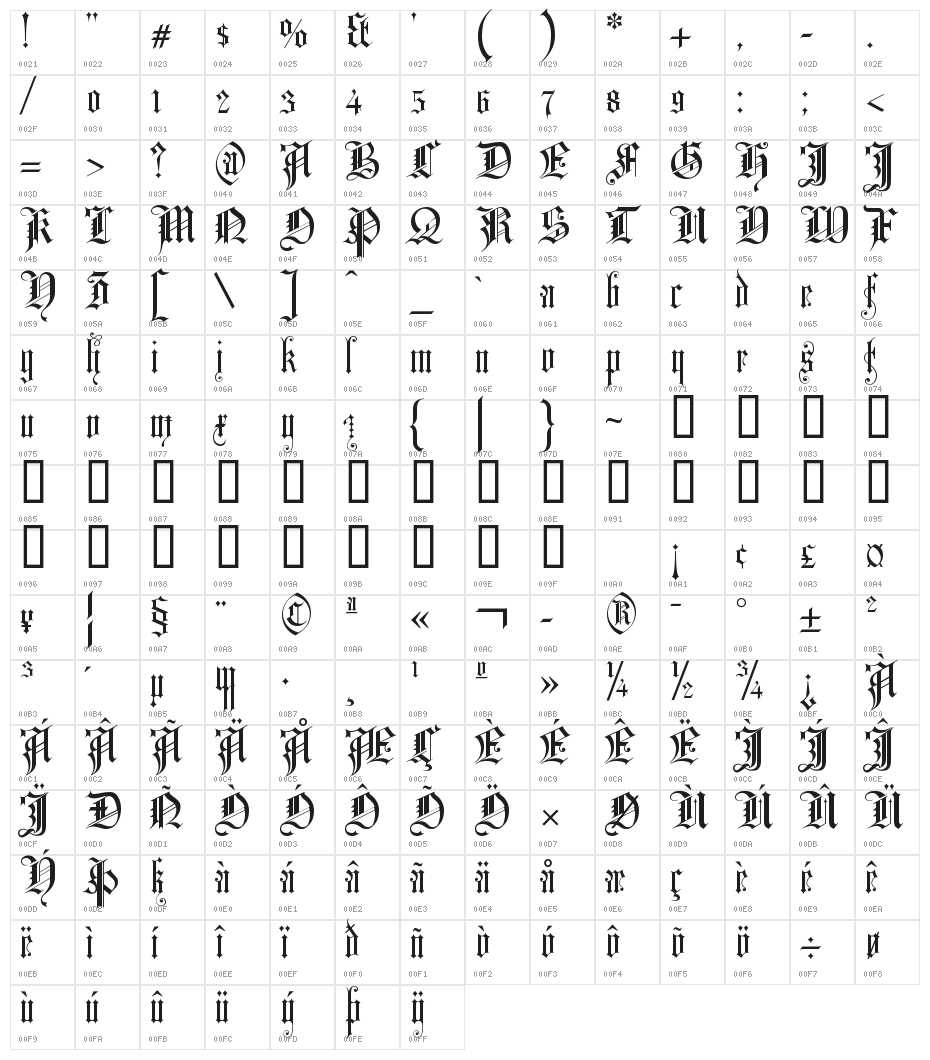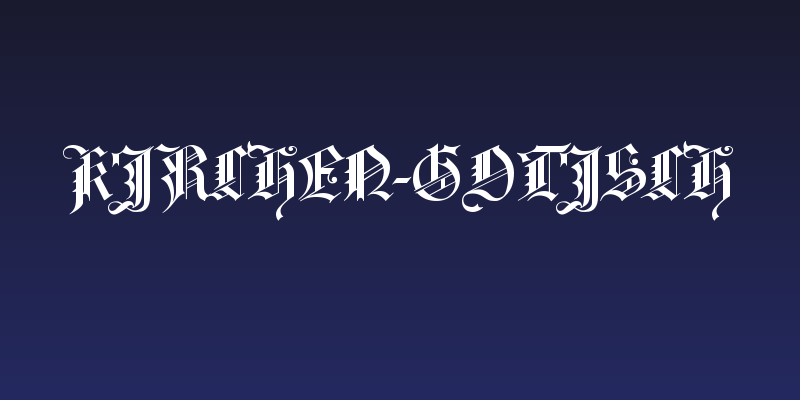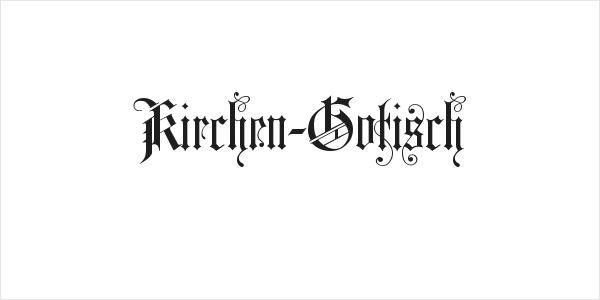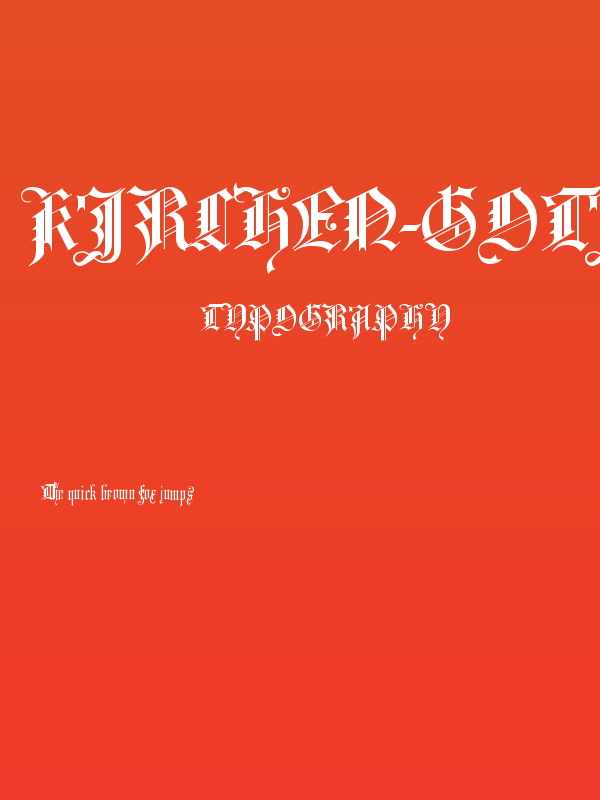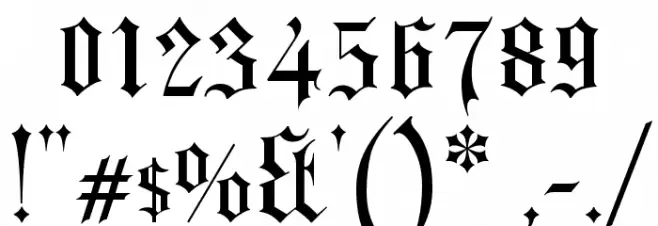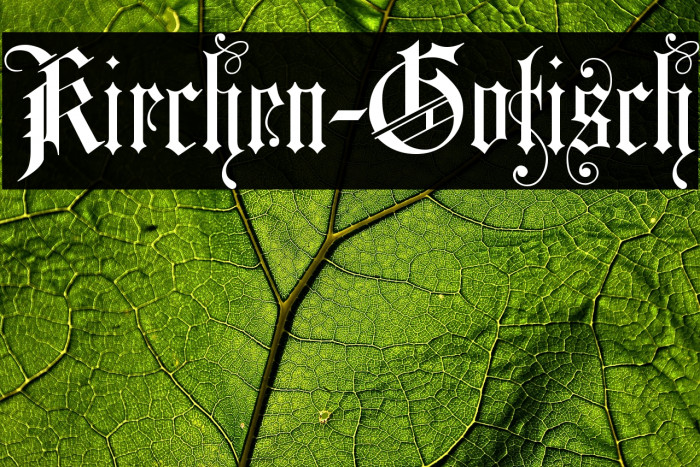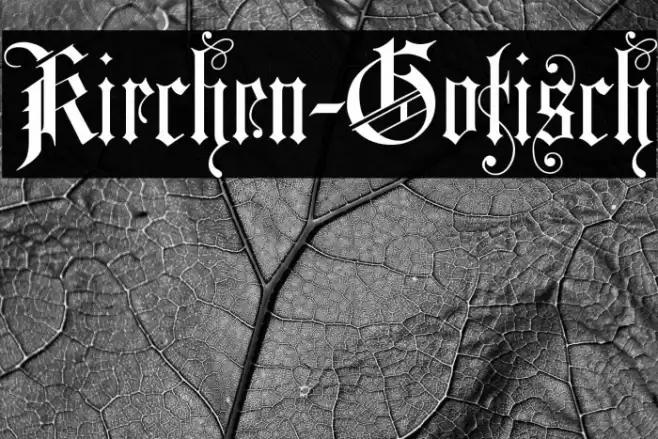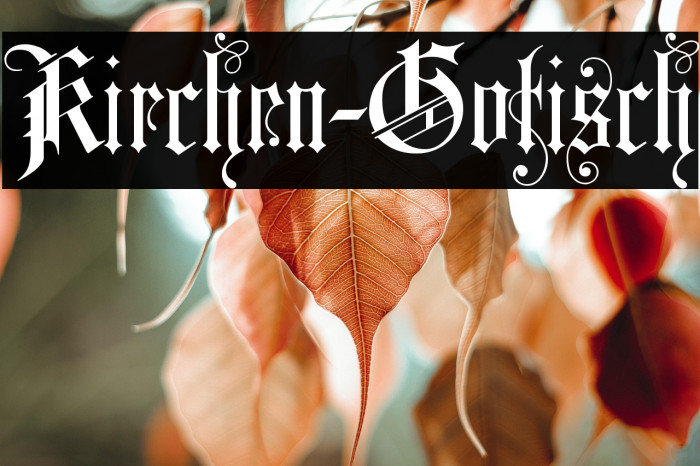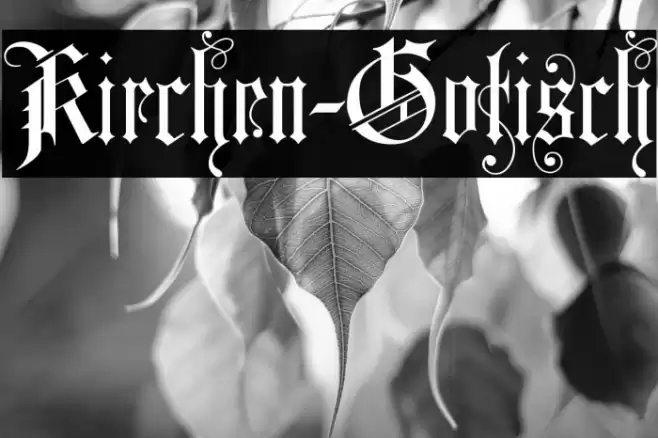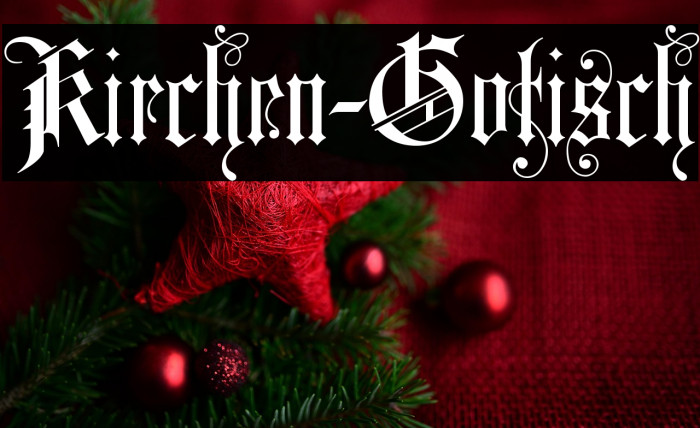
Kirchen-Gotisch Font
✎ Gothic
| Kategorien | Gothic |
| Gesamtstil | Vintage |
| Vorgeschlagene Projekte | Ideal for historical documents, wedding invitations, book covers, and branding that requires a gothic or medieval touch. |